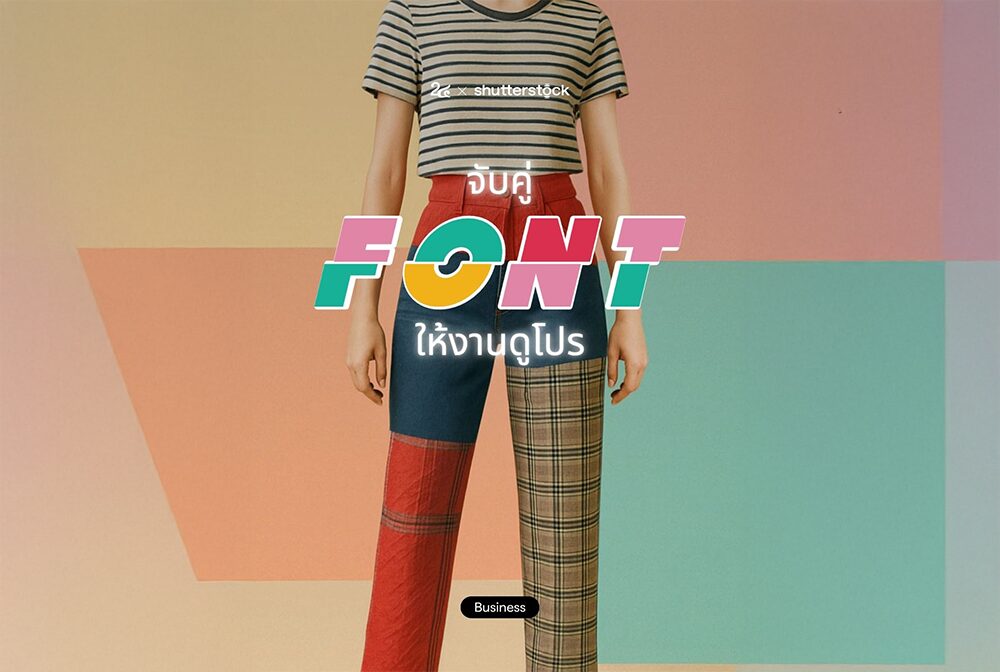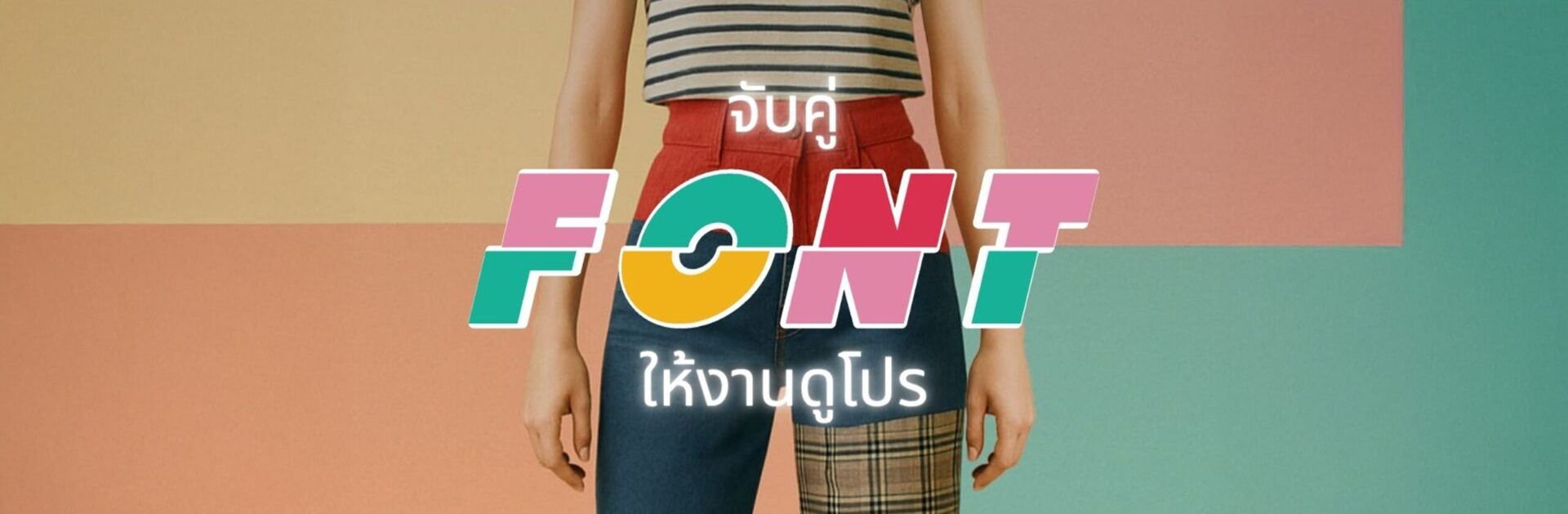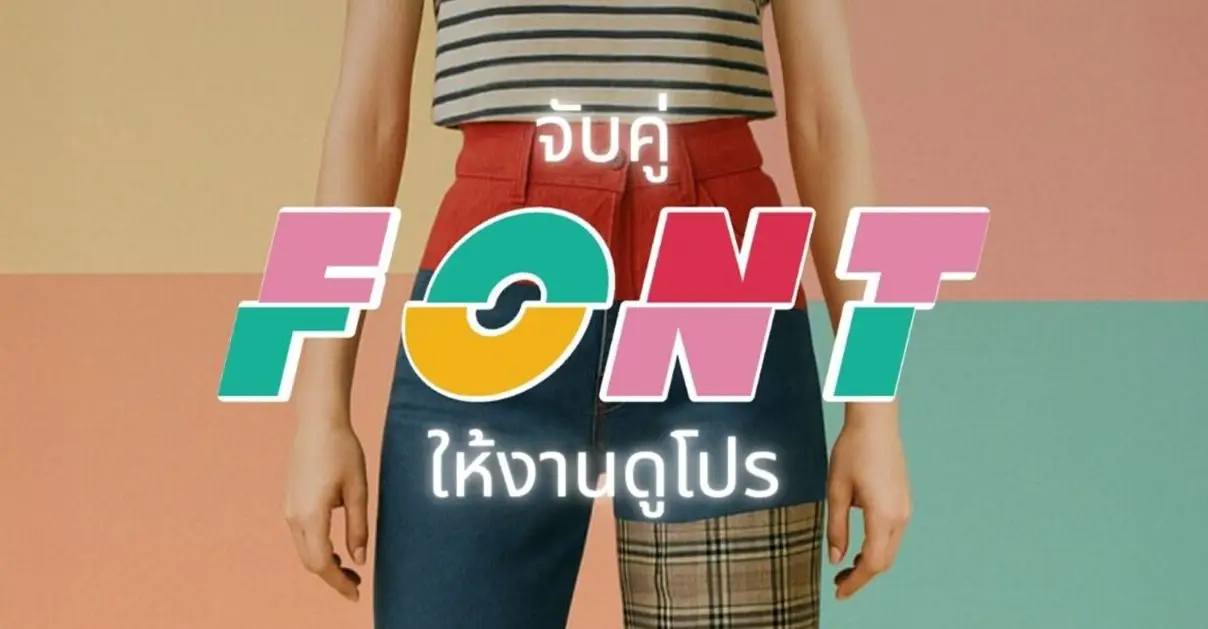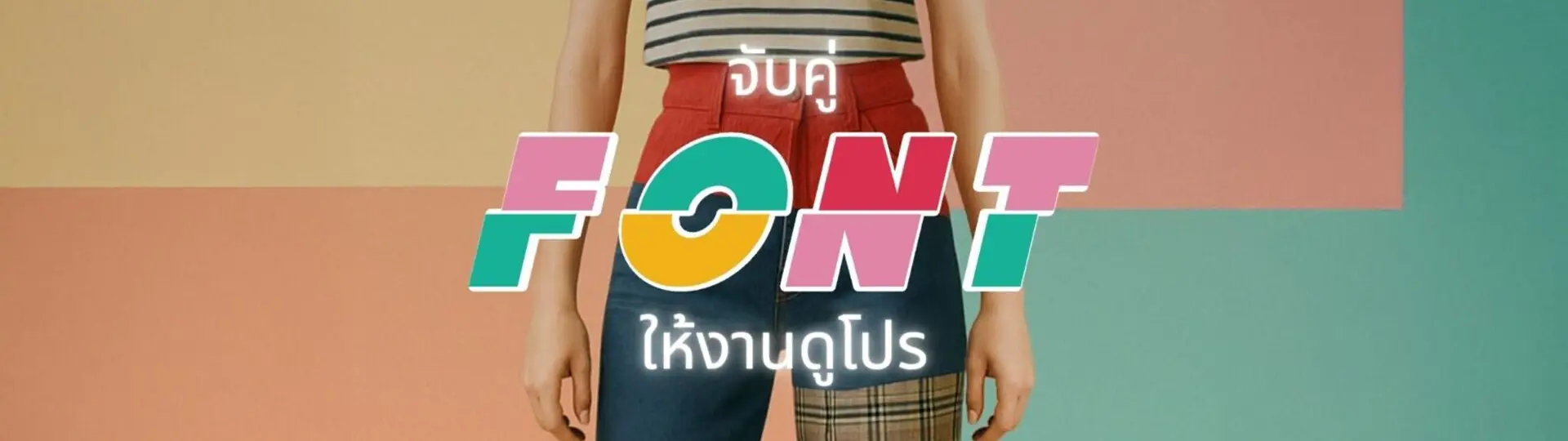
จับคู่ฟอนต์ให้ตรงฟีล: ใช้ฟอนต์ยังไง? ให้อารมณ์ตรงใจกลุ่มเป้าหมาย
ถ้าถามว่า “ฟอนต์” คืออะไร หลายคนอาจนึกถึงแค่ตัวหนังสือที่เราเห็นในงานกราฟิกหรือในเว็บไซด์ แต่จริง ๆ ฟอนต์มีบทบาทเหมือน “น้ำเสียง” หรือ “บุคลิก” ของข้อความที่ทำให้งานกราฟิกมีชีวิตและความหมาย ฟอนต์ไม่ได้แค่บอกว่าให้เราอ่านอะไร แต่ยังบอกว่าเราควรรู้สึกยังไงกับสิ่งนั้น
และที่สำคัญกว่านั้นคือ “การจับคู่ฟอนต์” คือกุญแจสำคัญที่จะช่วยสร้างความสมดุลในงาน เพราะไม่ใช่แค่ฟอนต์เดียวที่ทำงานได้ดี แต่เป็นการเลือกและจับคู่ฟอนต์หลายแบบให้เข้ากันอย่างลงตัวต่างหากที่จะทำให้งานดูมืออาชีพ สมูธ และสื่อสารอารมณ์ได้ชัดเจน
ทำไมจับคู่ฟอนต์ถึงสำคัญ?
ลองนึกภาพว่าแต่ละฟอนต์คือ “ชุดแต่งตัว” ของตัวอักษรที่เราใช้ในงานดีไซน์ ทุกฟอนต์มีสไตล์ บุคลิก และอารมณ์ในตัวเองเหมือนคนเราที่เลือกใส่ชุดตามโอกาส หรือความรู้สึกในวันนั้น ๆ
ถ้าเราใส่ชุดทำงานไปงานปาร์ตี้ ชุดมันอาจจะดูไม่เหมาะ ไม่เข้ากับบรรยากาศ หรือถ้าใส่ชุดลำลองไปงานเลี้ยงสังสรรค์แบบทางการ หลานคนก็อาจรู้สึกว่า “ทำไมถึงแต่งตัวแบบนี้มางานนี้?” เป็นต้น
ฟอนต์ก็เหมือนกัน ถ้าเลือกฟอนต์มาใช้แบบไม่เข้ากับคาแรคเตอร์ของงาน หรือกลุ่มเป้าหมาย เราก็เหมือนใส่ชุดผิดธีมให้ตัวอักษร ผลลัพธ์คือคนดูจะรู้สึกสับสน ไม่เข้าใจว่าเรากำลังสื่อสารอะไร หรือแม้กระทั่งรู้สึกว่า “งานนี้ดูไม่มืออาชีพ”
แต่ถ้าเราจับคู่ฟอนต์ได้ถูกใจ ได้ฟอนต์ที่เข้ากัน มีความสมดุล และเหมาะกับอารมณ์ของงานเหมือนกับเลือกชุดที่เข้ากับธีมงานจริง ๆ สิ่งที่จะเกิดขึ้นคือ
• งานจะดูลื่นไหล ไม่มีอะไรสะดุดหรือขัดตา
• ข้อความอ่านง่าย ไม่ทำให้คนอ่านต้องหยุดคิดว่าควรอ่านยังไง
• อารมณ์และบุคลิกของงานถูกถ่ายทอดออกมาอย่างชัดเจน
• ช่วยให้สื่อสารกับกลุ่มเป้าหมายได้ตรงใจมากขึ้น เพราะฟอนต์เปรียบเสมือน “เสียง” ที่แทนคำพูดในงานนั้น ๆ
ลักษณะของฟอนต์ส่งผลต่ออารมณ์ยังไงบ้าง?
ฟอนต์แต่ละแบบมี “บุคลิก” และ “อารมณ์” ที่แตกต่างกัน ซึ่งส่งผลโดยตรงต่อความรู้สึกของคนอ่าน งานดีไซน์เลยต้องเลือกฟอนต์ให้เหมาะกับสิ่งที่อยากสื่อ นี่คือภาพรวมของลักษณะฟอนต์หลัก ๆ ที่เรามักเจอและความรู้สึกที่ฟอนต์สื่อสารออกมา
1. ฟอนต์แบบ Serif (มีขีดหรือตัวหนอนเล็ก ๆ ปลายตัวอักษร)
ฟอนต์แนวนี้จะให้ความรู้สึกคลาสสิก เรียบร้อย และน่าเชื่อถือ เหมาะกับงานที่ต้องการความเป็นทางการ ความเก่าแก่ หรือความมั่นคง เช่น งานเอกสาร การ์ดเชิญแบบหรู ๆ หรือแบรนด์ที่เน้นความน่าเชื่อถือ
2. ฟอนต์แบบ Sans-Serif (ไม่มีขีดปลายตัวอักษร)
ดูทันสมัย เรียบง่าย สะอาดตา เหมาะกับงานที่ต้องการความรู้สึกสดใหม่ หรือดูเทคโนโลยี เช่น เว็บไซด์บริษัทสตาร์ทอัพ แอปฯ หรือแบรนด์ที่เน้นความล้ำสมัย
3. ฟอนต์แบบ Script (แบบลายมือหรือตัวเขียนเชื่อมต่อกัน)
ส่งอารมณ์อบอุ่น เป็นกันเอง หรือโรแมนติก เหมาะกับงานเชิญงานแต่งงาน การ์ด หรือแบรนด์ที่อยากสื่อความนุ่มนวลและเป็นมิตร
4. ฟอนต์แบบ Display (ฟอนต์ตกแต่งแบบแปลกตา)
ฟอนต์กลุ่มนี้มักใช้เพื่อดึงความสนใจ เหมาะกับงานโฆษณา ปกหนังสือ หรือโปสเตอร์ที่ต้องการความโดดเด่นและสนุกสนาน แต่ถ้าใช้เยอะเกินไปจะทำให้อ่านยากและรกตาได้
5. ฟอนต์แบบ Monospace (ตัวอักษรมีความกว้างเท่ากันทุกตัว)
ให้ความรู้สึกเทคนิค เทคโนโลยี หรือความเป็นมืออาชีพด้านโปรแกรมมิ่ง เหมาะกับงานที่เกี่ยวข้องกับคอมพิวเตอร์ โค้ดดิ้ง หรือเอกสารทางเทคนิค
ตัวอย่างการจับคู่ฟอนต์ที่ได้ผลดี
1. ฟอนต์ Serif + Sans-Serif
จับคู่ฟอนต์คลาสสิกกับฟอนต์โมเดิร์น เป็นคู่ที่ใช้บ่อยมาก เพราะบาลานซ์กันได้ดี
ตัวอย่าง:
• Playfair Display (Serif) + Montserrat (Sans-Serif)
• Merriweather (Serif) + Open Sans (Sans-Serif)
ความรู้สึก: ดูทันสมัยแต่ยังคงความน่าเชื่อถือ เหมาะกับเว็บข่าว เว็บไซต์แบรนด์แฟชั่น หรือบล็อก
2. Sans-Serif + Sans-Serif (คู่สะอาดตา)
จับคู่ฟอนต์ไร้ขีดที่เข้ากัน ดูเรียบง่าย สะอาดตา เหมาะกับงานเทคโนโลยี หรือแอปพลิเคชัน
ตัวอย่าง:
• Roboto + Lato
• Helvetica Neue + Arial
ความรู้สึก: สดใหม่ เป็นกันเอง และเข้ากับงานที่ต้องการความลื่นไหลของข้อมูล
3. Serif + Script (ทางการแต่เป็นมิตร)
ฟอนต์ที่ดูเป็นทางการมาผสมกับลายมือที่นุ่มนวล เหมาะกับการ์ดเชิญ งานแต่ง หรืองานที่ต้องการความโรแมนติก
ตัวอย่าง:
• Georgia + Pacifico
• Times New Roman + Dancing Script
ความรู้สึก: เป็นทางการแต่ไม่แข็งทื่อ เพิ่มความเป็นมิตรและอบอุ่น
4. Display + Sans-Serif (ฟอนต์เด่นคู่กับอ่านง่าย)
ใช้ฟอนต์โชว์เอกลักษณ์ในหัวข้อผสมกับฟอนต์อ่านง่ายสำหรับเนื้อหา
ตัวอย่าง:
• Oswald + Raleway
• Bebas Neue + Open Sans
ความรู้สึก: ดึงดูดสายตาแต่ไม่ลายตา เหมาะกับโปสเตอร์และโฆษณา
จับคู่ฟอนต์คือเรื่องของการบาลานซ์ให้ฟอนต์สองแบบหรือมากกว่านั้นทำงานร่วมกันได้ดี ไม่แข่งกันแย่งความสนใจ แต่ช่วยเสริมให้งานดูดีและสื่อสารอารมณ์ได้ชัดเจน